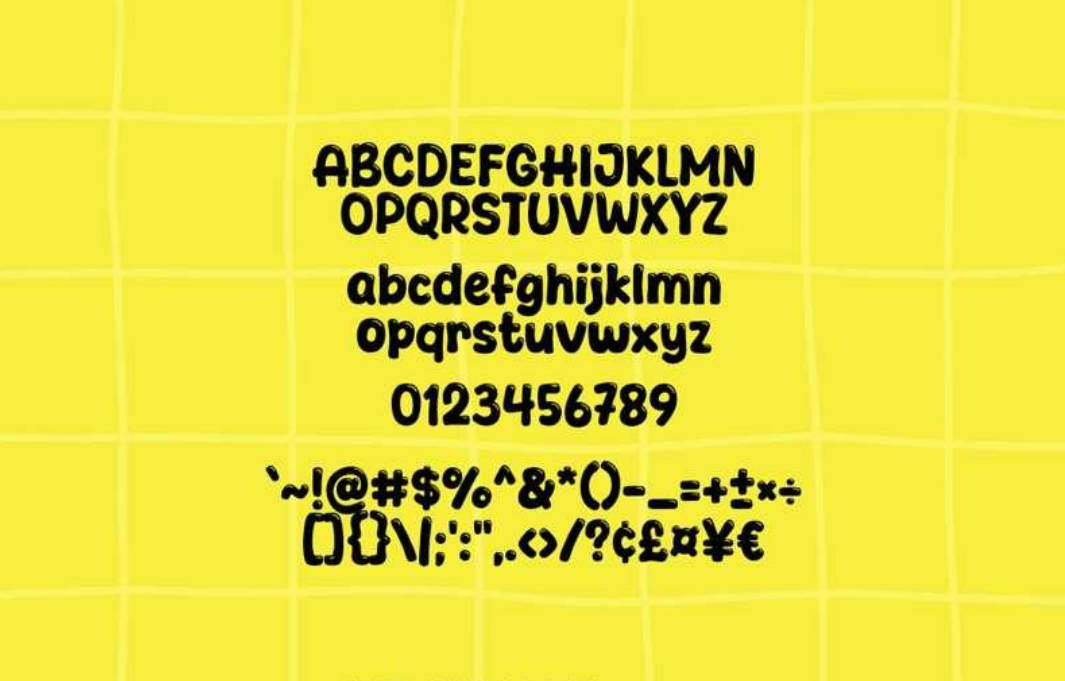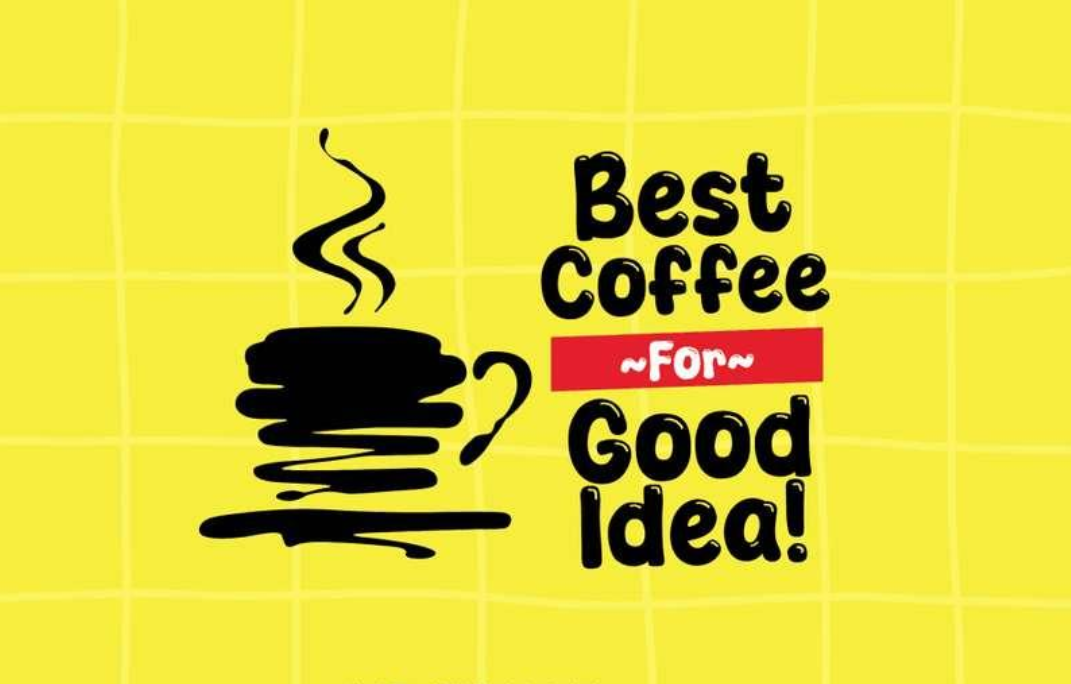
Howdybun 卡通圆润免费英文字体下载
Howdybun 是 Khurasan 推出的圆润泡泡卡通英文字体,笔画厚实软糯,充满童趣棉花糖质感,个人与商业使用完全免费。适合公众号封面、短视频标题、文创海报、LOGO 设计,仅支持英文、数字与标点。
Howdybun是一款带有时尚潮流科技感的英文字体,字形优雅,该款字体文件格式为TTF,该字体适合作为标题字,可广泛用于海报、品牌和媒体等宣传方面的使用。
不管是做桌游卡牌、电影海报,还是设计文具、包装,甚至是书籍杂志的编辑印刷,用它都超合适!不想让排版太死板,又想保证视觉辨识度的宝子,直接冲就对了!